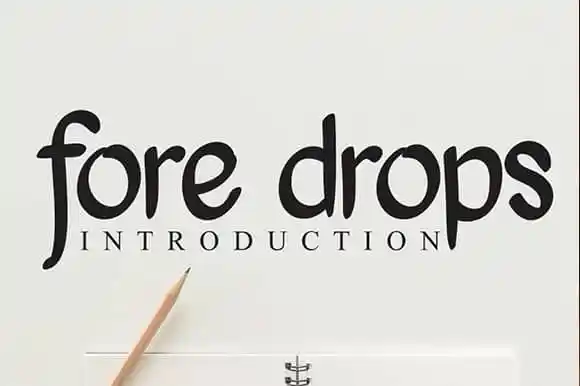
Fore Drops Script Font – Download Grátis
A novíssima fonte ‘Fore Drops Script Font’ é perfeita para quem procura uma linguagem suave e elegante, ideal para diversos projetos que exigem a delicadeza de uma escrita à mão. A categoria de estilo desta fonte é a Handwritten Fonts, criada pelo designer andikastudio. Esta fonte é especialmente versátil e atende a um vasto leque de aplicações, desde os postais e as embalagens até as campanhas nas redes sociais. Perfeita para criar logos que destacam suas marcas ou peças de design para sites e revistas. Além disso, é ideal para aqueles interessados em incorporar um toque pessoal à sua arte digital, como no uso de fontes de papelada ou mesmo na criação de assinaturas distintivas. O estilo elegante e delicado desta fonte torna-a uma ótima opção para qualquer projeto que precise apresentar-se com a autenticidade de uma escrita à mão. Seja em um design gráfico sofisticado, arte digital minimalista ou até mesmo em seu próprio branding personalizado, esta font será certamente um elemento essencial na sua próxima criação artística.